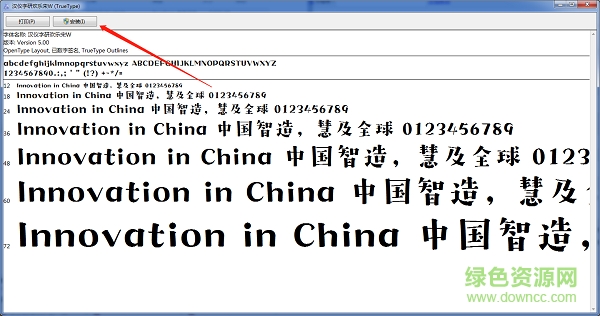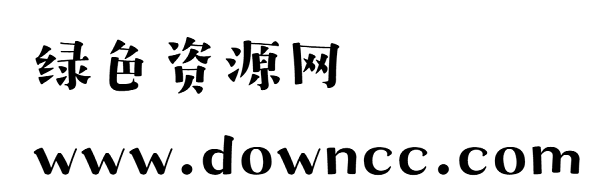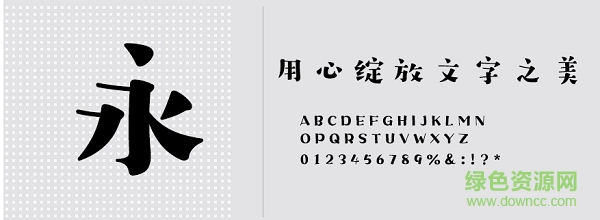
漢儀字研歡樂(lè)宋w字體
漢儀字研歡樂(lè)宋w字體是一款適用面廣,結(jié)構(gòu)簡(jiǎn)單的字體,字體整體看起來(lái)教偏黑粗,所以使用的時(shí)候整個(gè)排版也會(huì)比較的濃密,非常適合標(biāo)題設(shè)計(jì)等等多個(gè)方便,喜歡的用戶快來(lái)綠色資源網(wǎng)下載吧!
漢儀字研歡樂(lè)w體簡(jiǎn)介:
漢儀字研歡樂(lè)宋W是漢儀字庫(kù)全新開(kāi)發(fā)的一款用于設(shè)計(jì)方面的創(chuàng)意字體,該字體線條圓潤(rùn),轉(zhuǎn)角以曲線處理,粗細(xì)搭配合理,整體效果非常出色,適用于高端時(shí)尚品牌產(chǎn)品的形象設(shè)計(jì)和推廣,具有較大范圍的應(yīng)用空間,有需要的朋友快來(lái)下載吧!
漢儀字研歡樂(lè)宋W預(yù)覽:
漢儀字研歡樂(lè)宋w字體